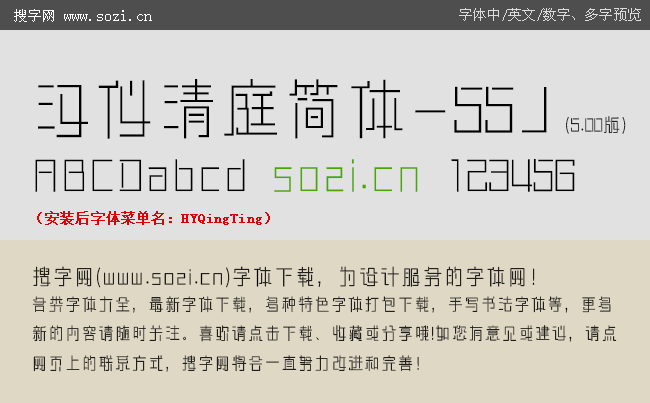
漢儀清庭簡體-55簡5.0版
搜字網(wǎng)提供一款漢儀清庭簡體-55簡5.0版中文字體下載,漢儀清庭體-55簡體字體是中文字體庫中的一款字體,字體看起來像是爬行出來的,每一筆的拐角都是90度,適合應(yīng)用于廣告設(shè)計(jì)、名片設(shè)計(jì)、包裝印刷、產(chǎn)品設(shè)計(jì)等應(yīng)用。